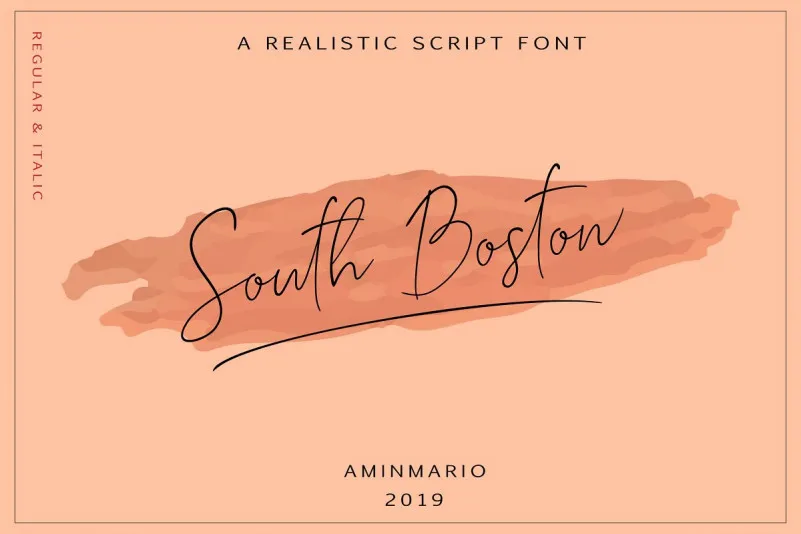
South Boston Script Font – Download Grátis
South Boston Script Font é uma elegante escolha para projetos que exigem sutileza e estilo. Desenvolvida pelo designer aminmario, esta fonte é inspirada em escrita manuscrita realista de South Boston, oferecendo um toque autêntico que se destaca dos demais. Ela apresenta linhas suaves, características próprias e uma base horizontal elegante que cria um visual distintivo e inovador. Seu estilo de texto de escrita gráfica dançante torna-o perfeito para aplicações como logotipos, assinaturas, branding, anúncios, cartões de visita, embalagens de casamento ou até mesmo em camisas e revistas. Suas características podem ser usadas em diversas plataformas, desde materiais impressos até mídia digital. Sem dúvida, é uma fonte perfeita para quem busca uma escrita manuscrita realista que transmite classe e originalidade.